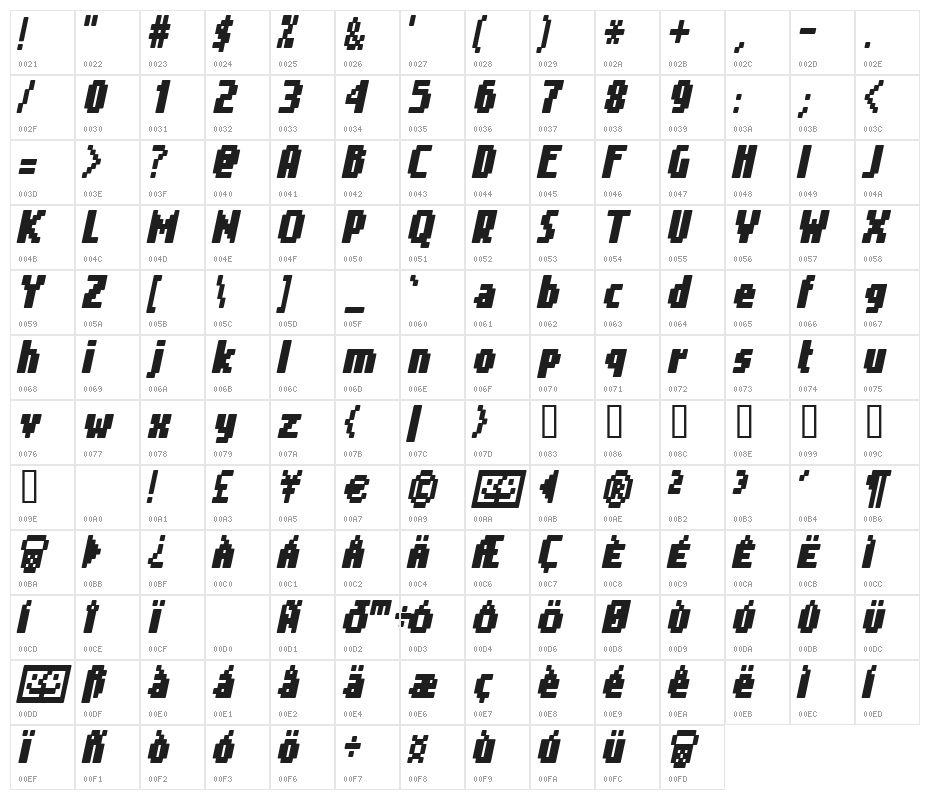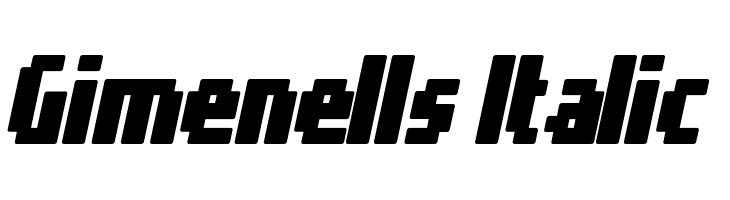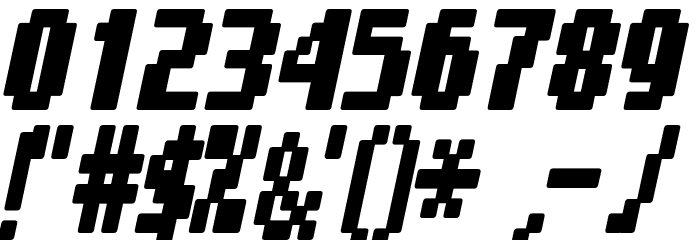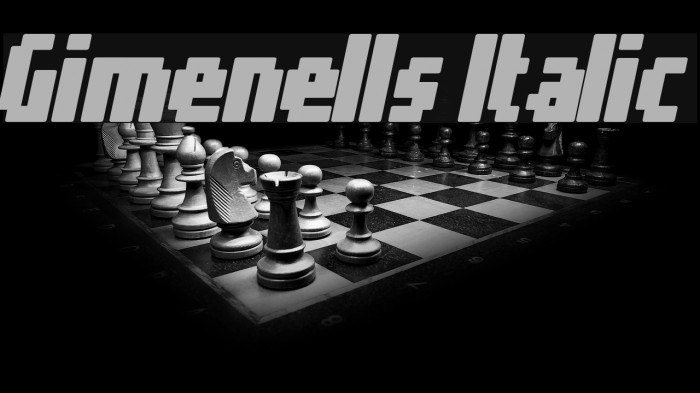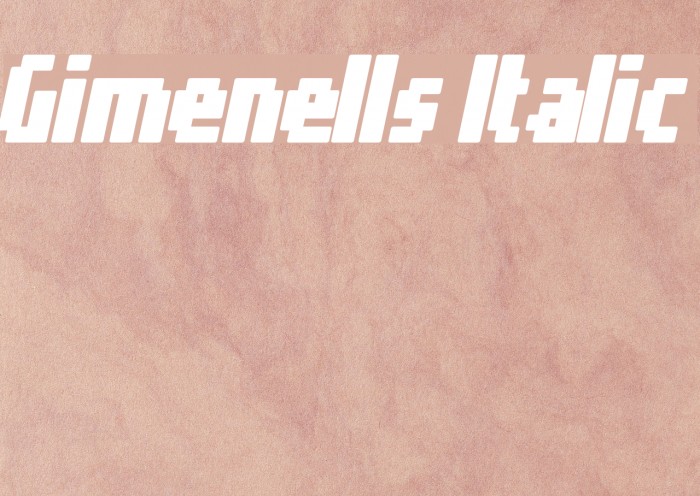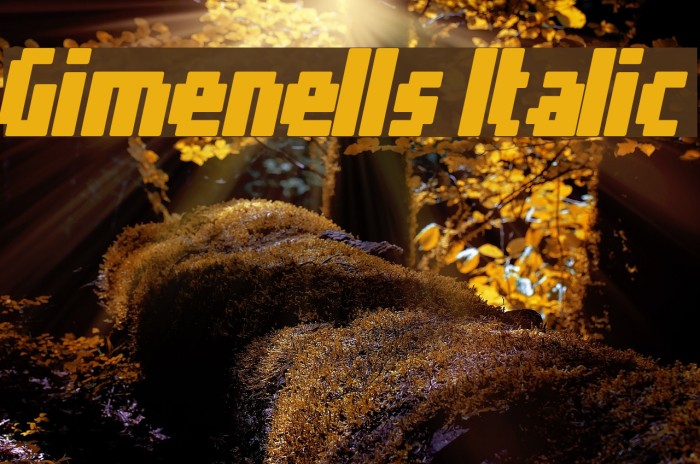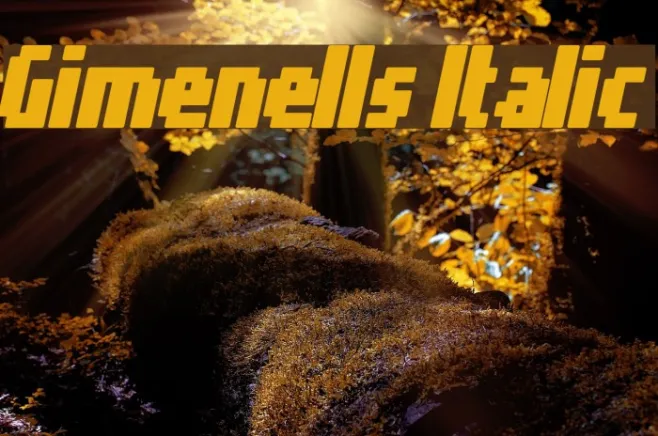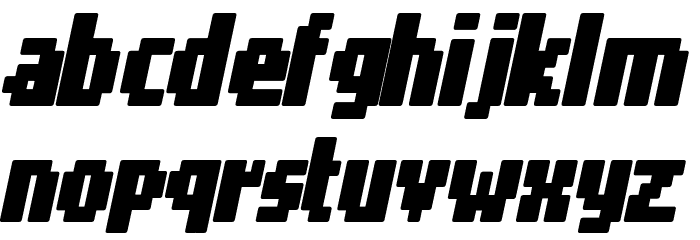
Gimenells Italic Font
| Projets proposés | Ideal for digital artwork, video game graphics, posters, and branding materials that require a bold and modern look. |